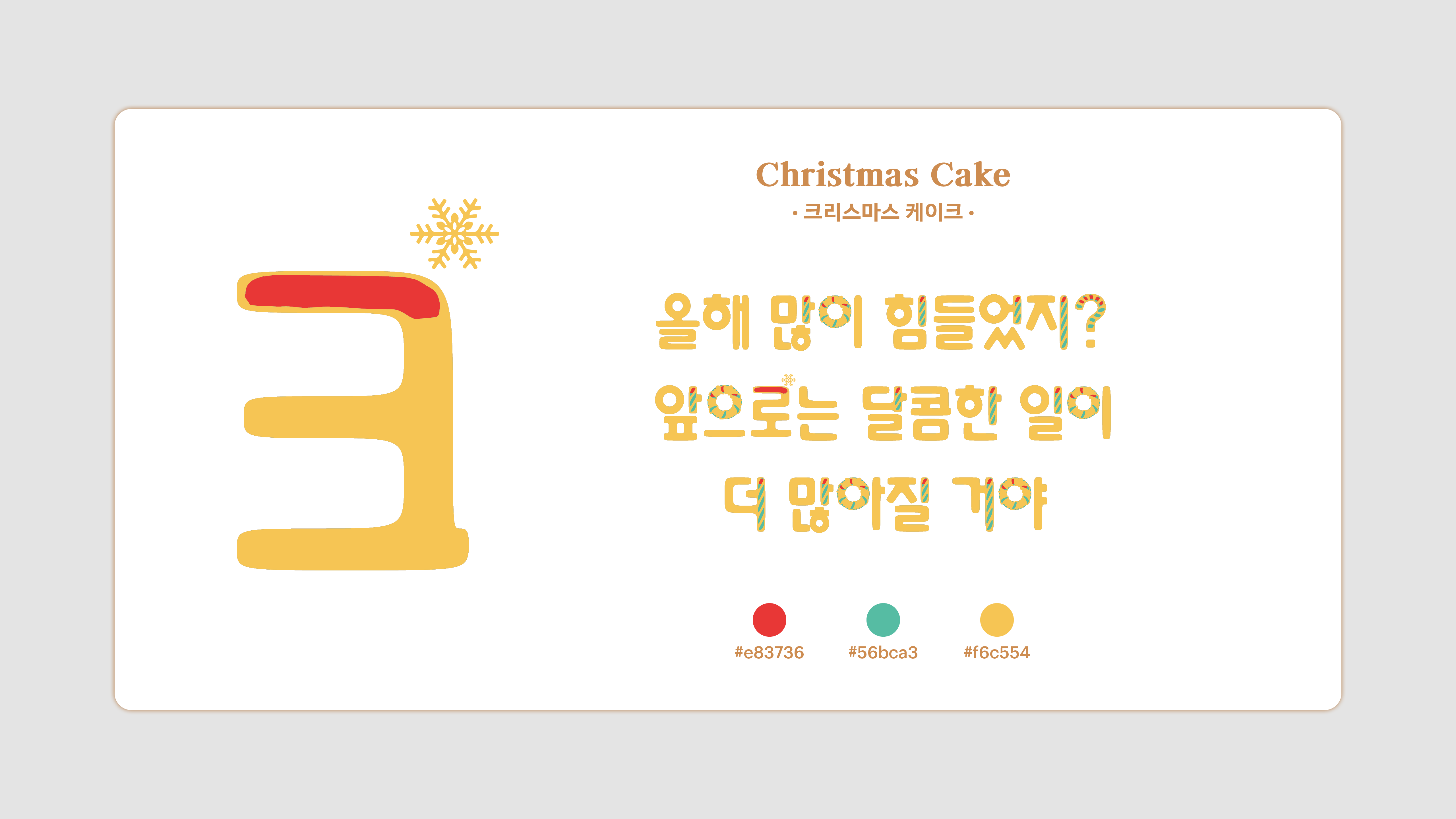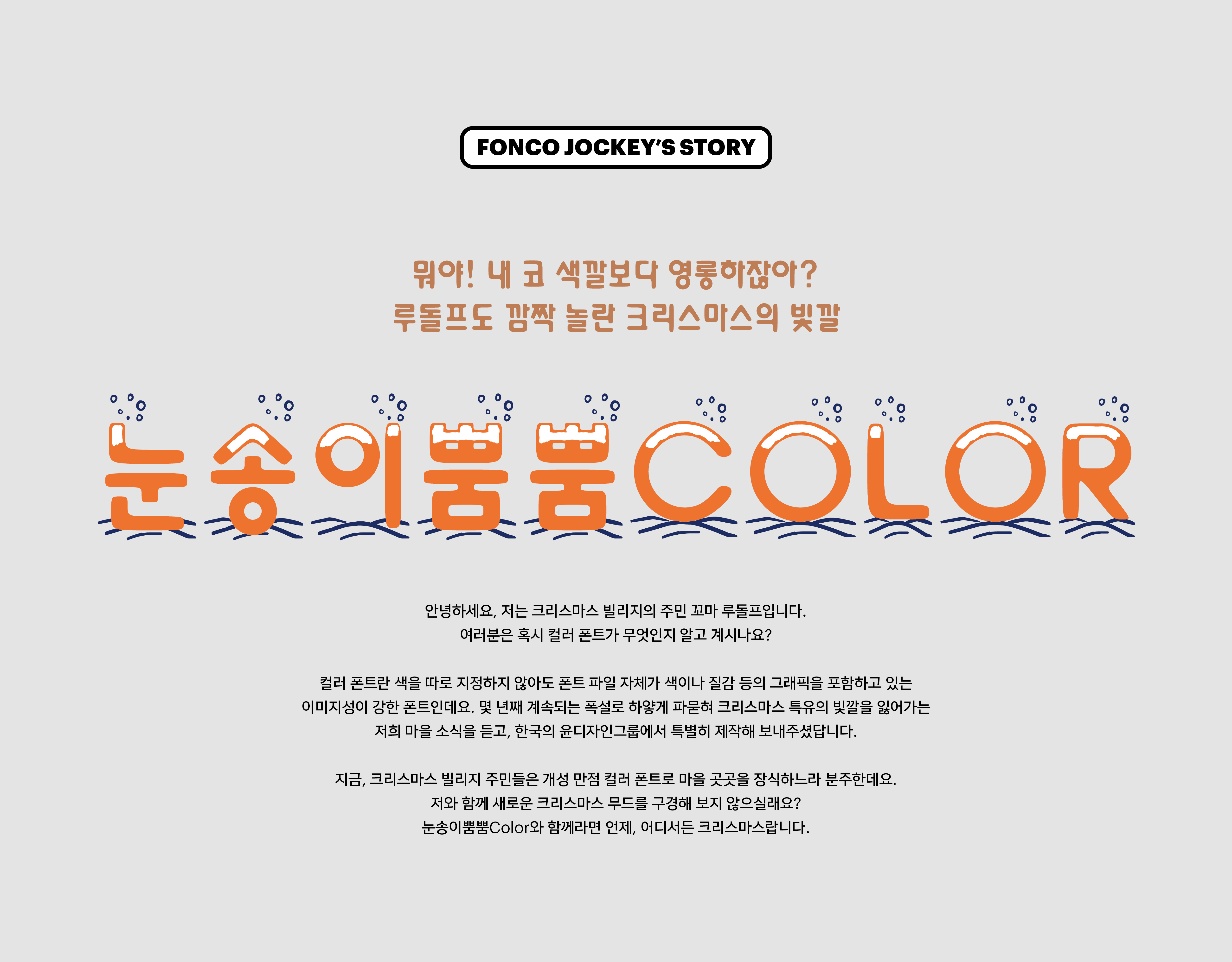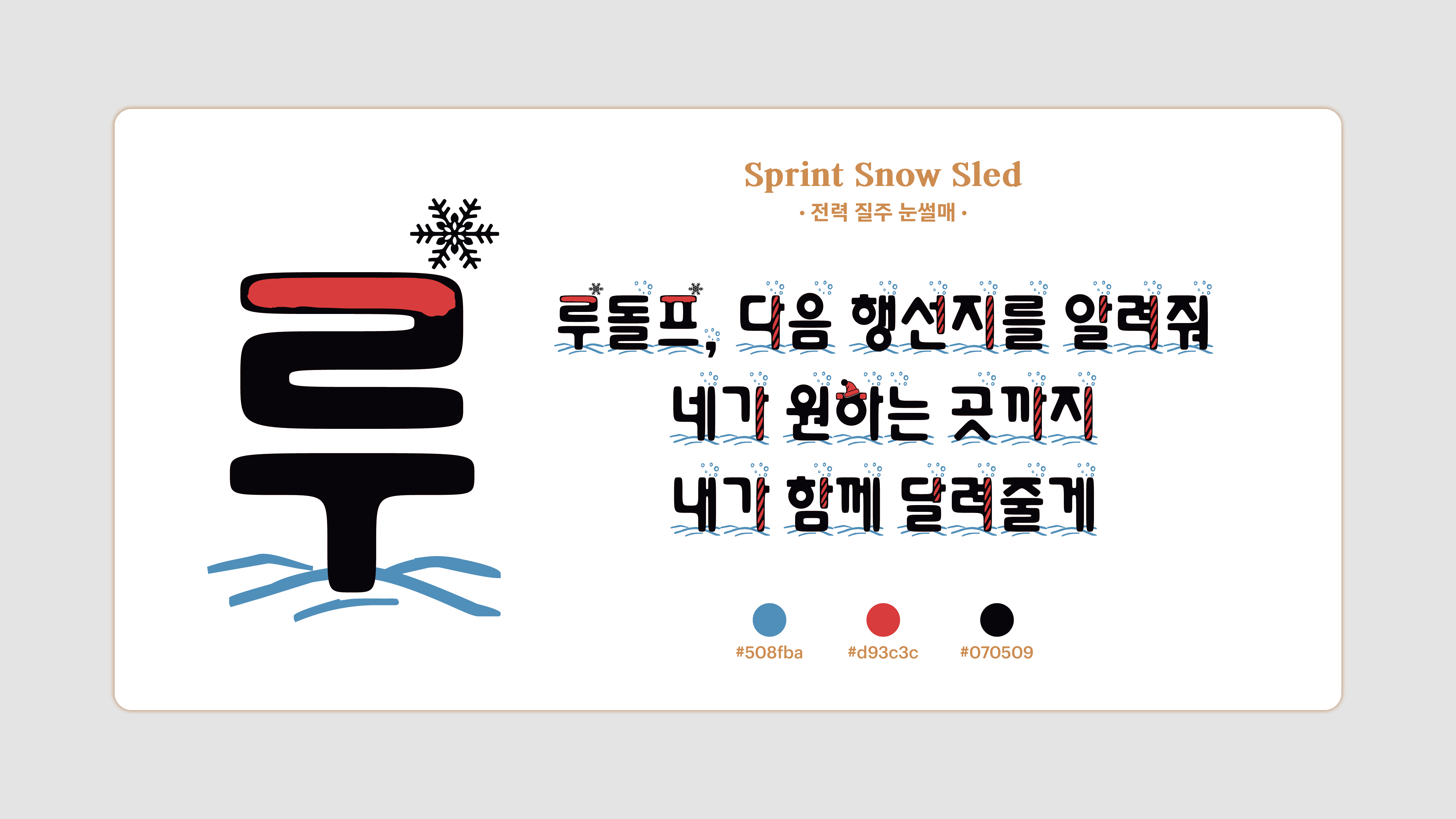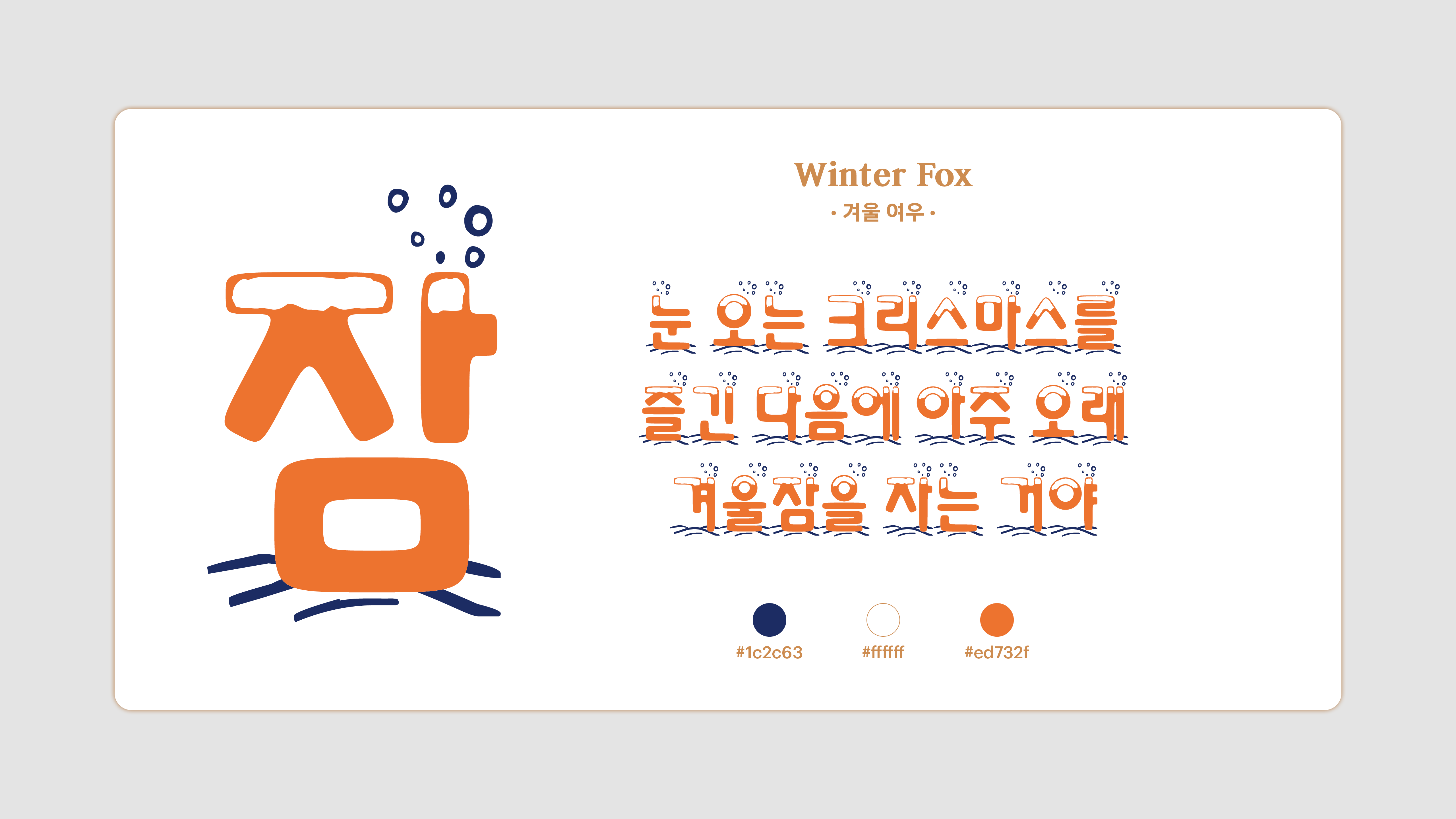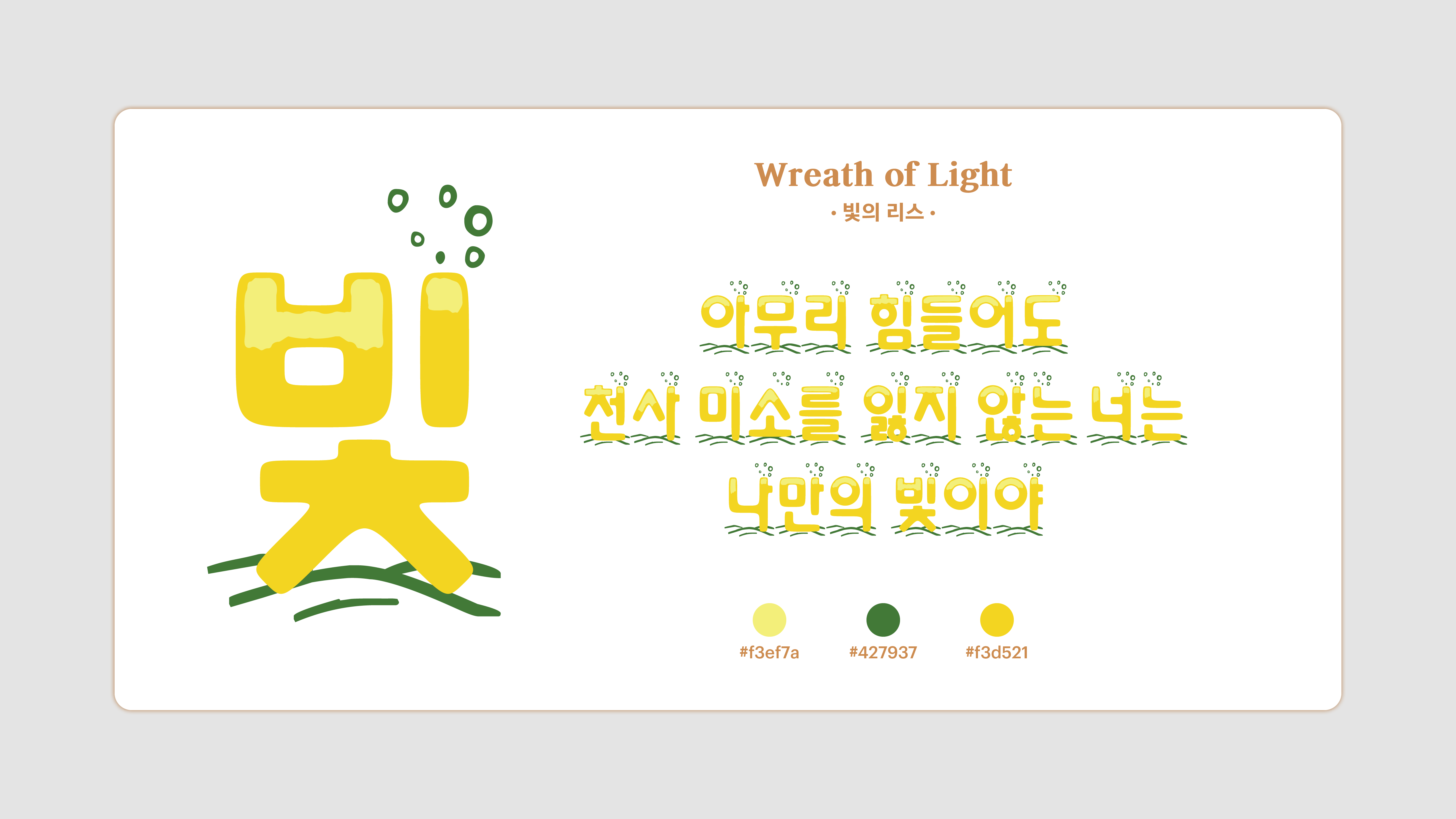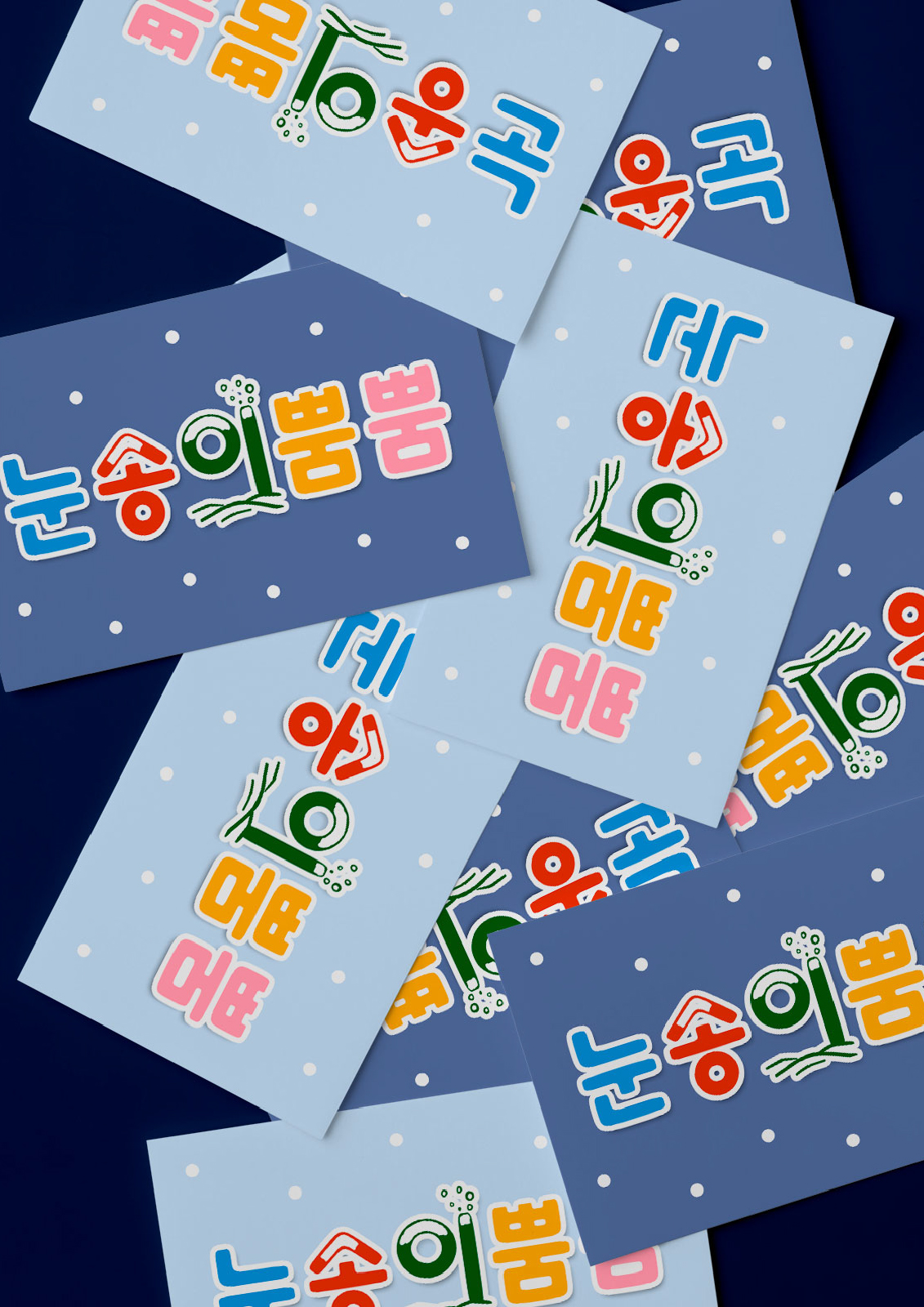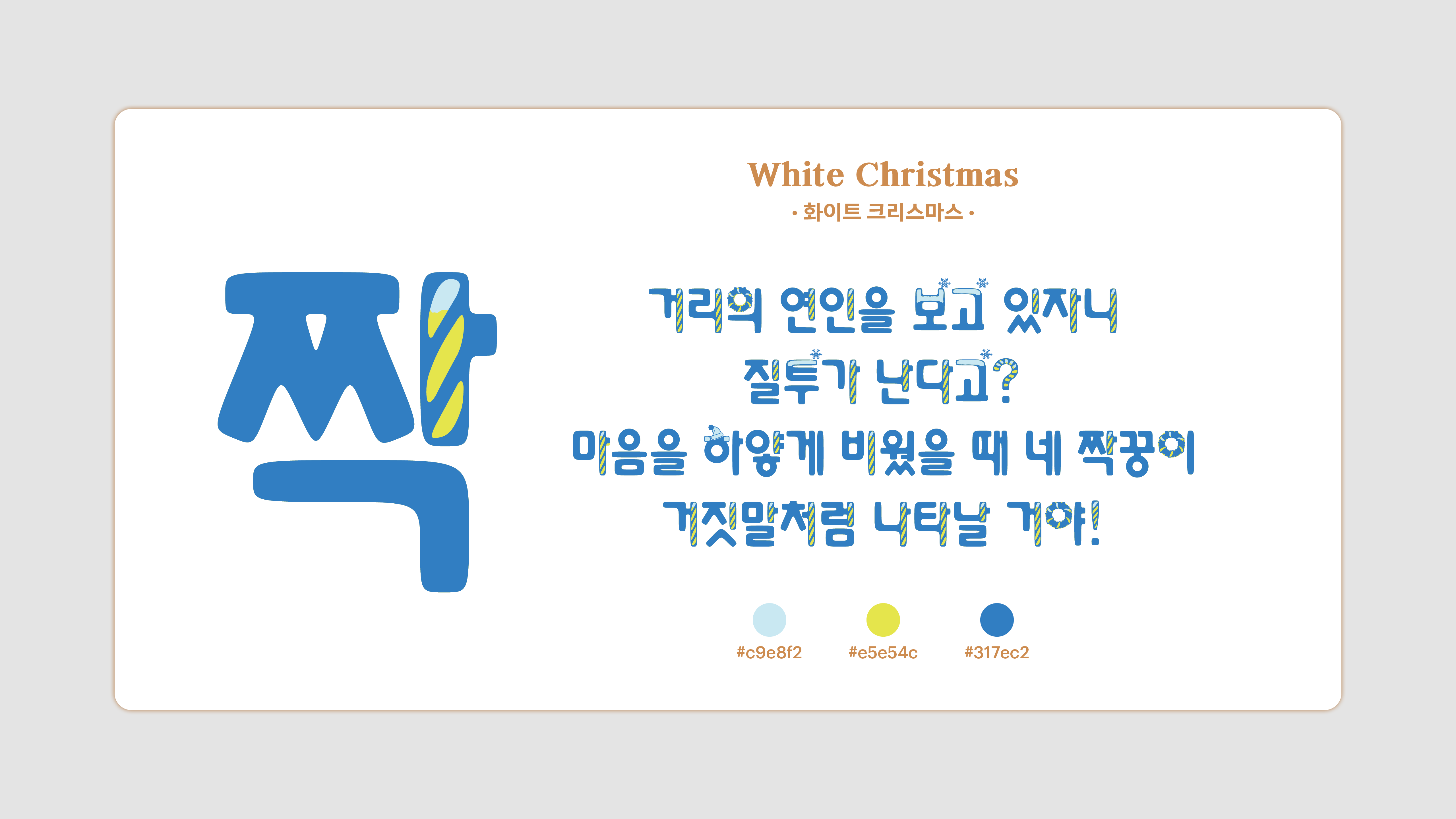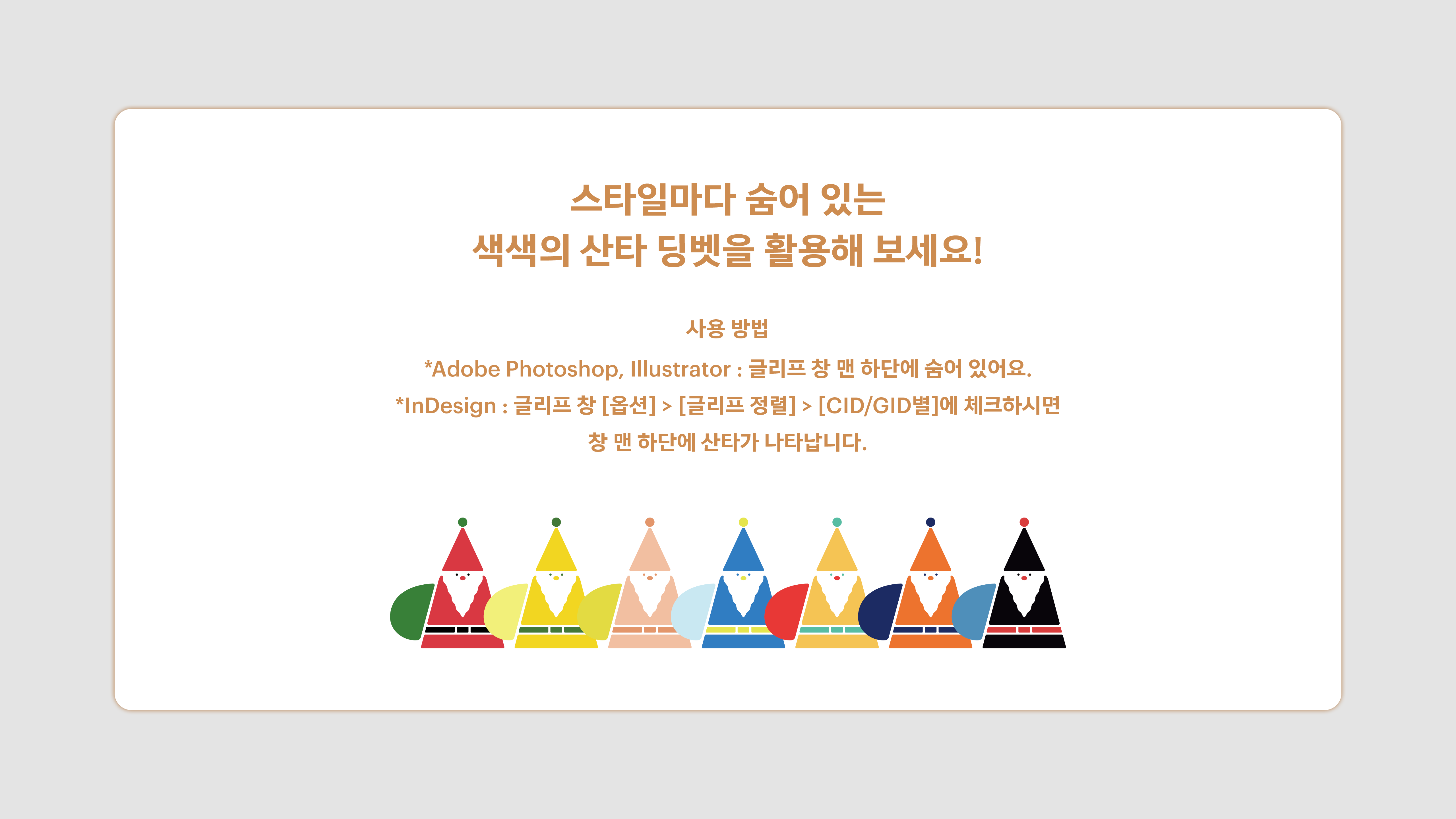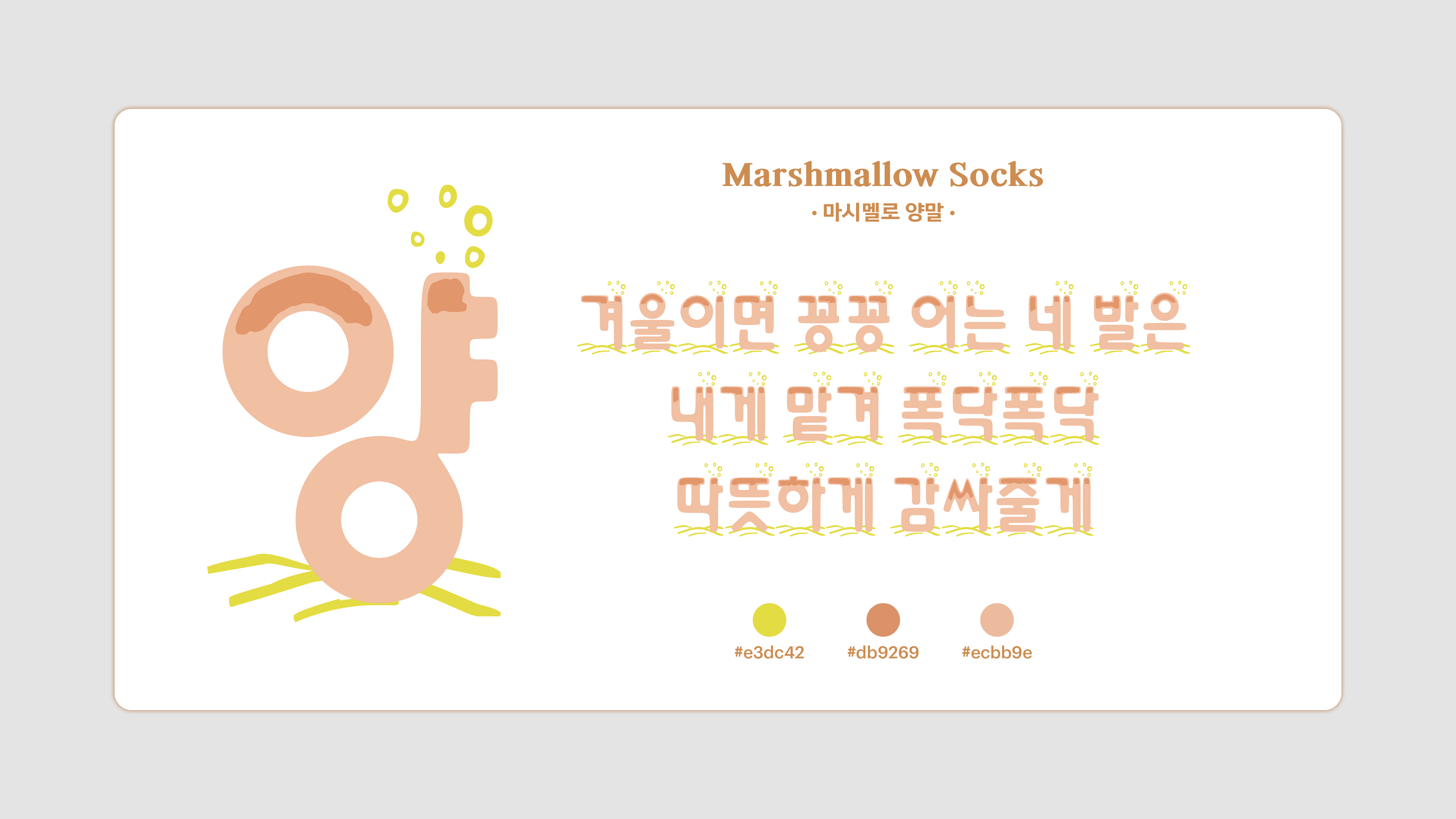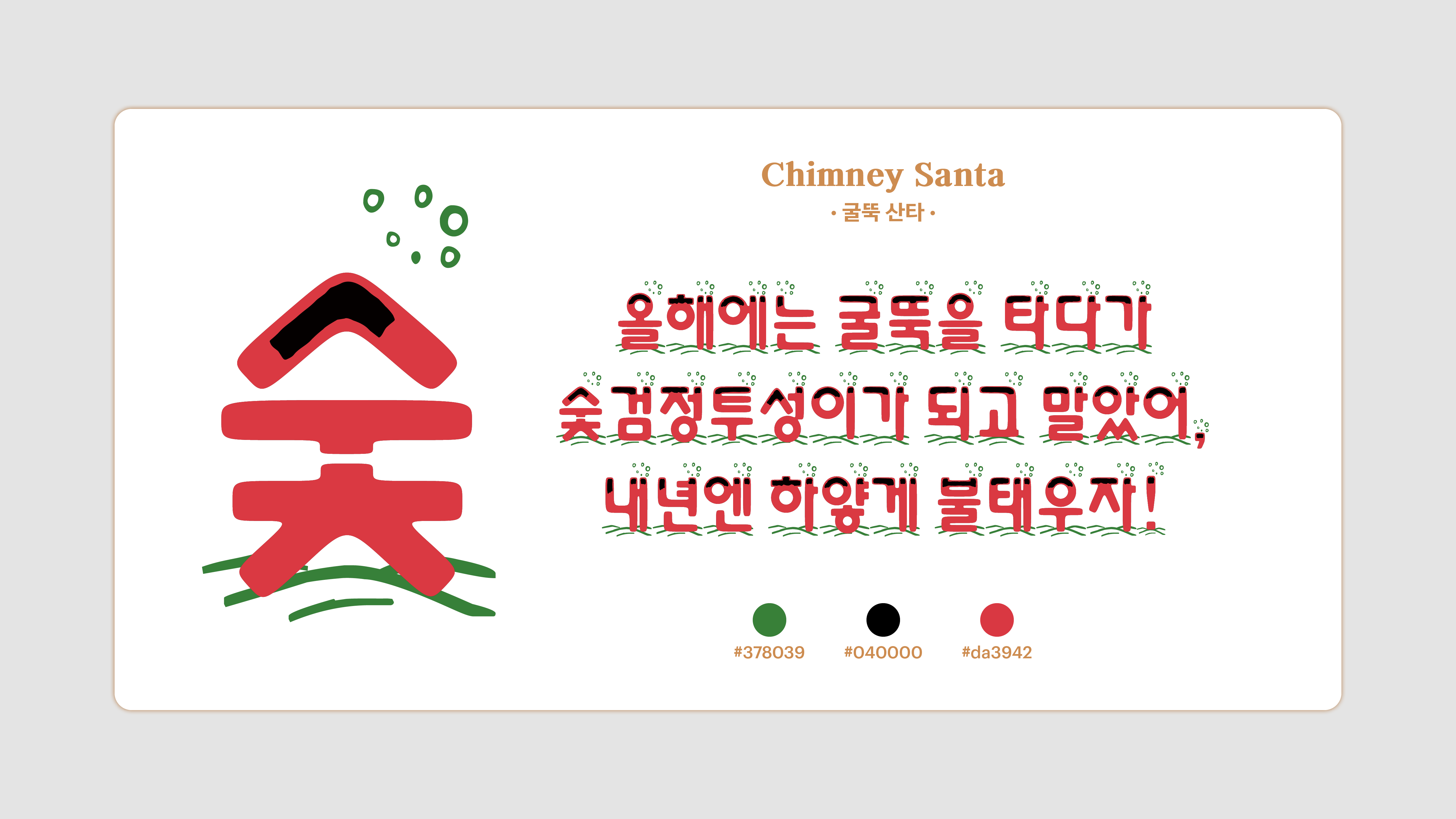
눈송이뿜뿜 Color
Yoon 눈송이뿜뿜 Color
컬러 폰트란 색을 따로 지정하지 않아도 폰트 파일 자체가 색이나 질감 등의 그래픽을 포함하고 있는 이미지성이 강한 폰트입니다. 굴뚝 산타, 빛의 리스, 마시멜로 양말, 화이트 크리스마스, 크리스마스 케이크, 겨울 여우, 전력 질주 눈썰매로 구성된 눈송이뿜뿜COLOR와 함께 언제 어디서나 크리스마스 무드를 만끽해보세요.